らくごえほん てんしき
KADOKAWAから絵本作家・川端誠氏著書による人気シリーズ「落語絵本」を新たな画風で7年ぶりに書き下ろした「らくごえほん てんしき」を発売された。
タイトルの「えんしき」は落語の演目で、絵本は考えたり笑いながら日本語の楽しさを学べる「落語の世界」を絵本で楽しめる内容になっている。
川端誠Profile●1952年、新潟県上越市生まれ。絵本作家。
作品に、『烏の島』(第5回絵本にっぽん賞受賞)『森の木』『びかびかぷつん』『十二支のお節料理』「お化け」シリーズ、「野菜忍列伝」シリーズ、『地球をほる』『槍ヶ岳山頂』(B L出版)、「落語絵本」シリーズ(クレヨンハウス)、「果物」シリーズ(文化出版局)など多数 。絵本作家ならではの絵本解説も好評。
タイトルの「てんしき(転失気)」とは?
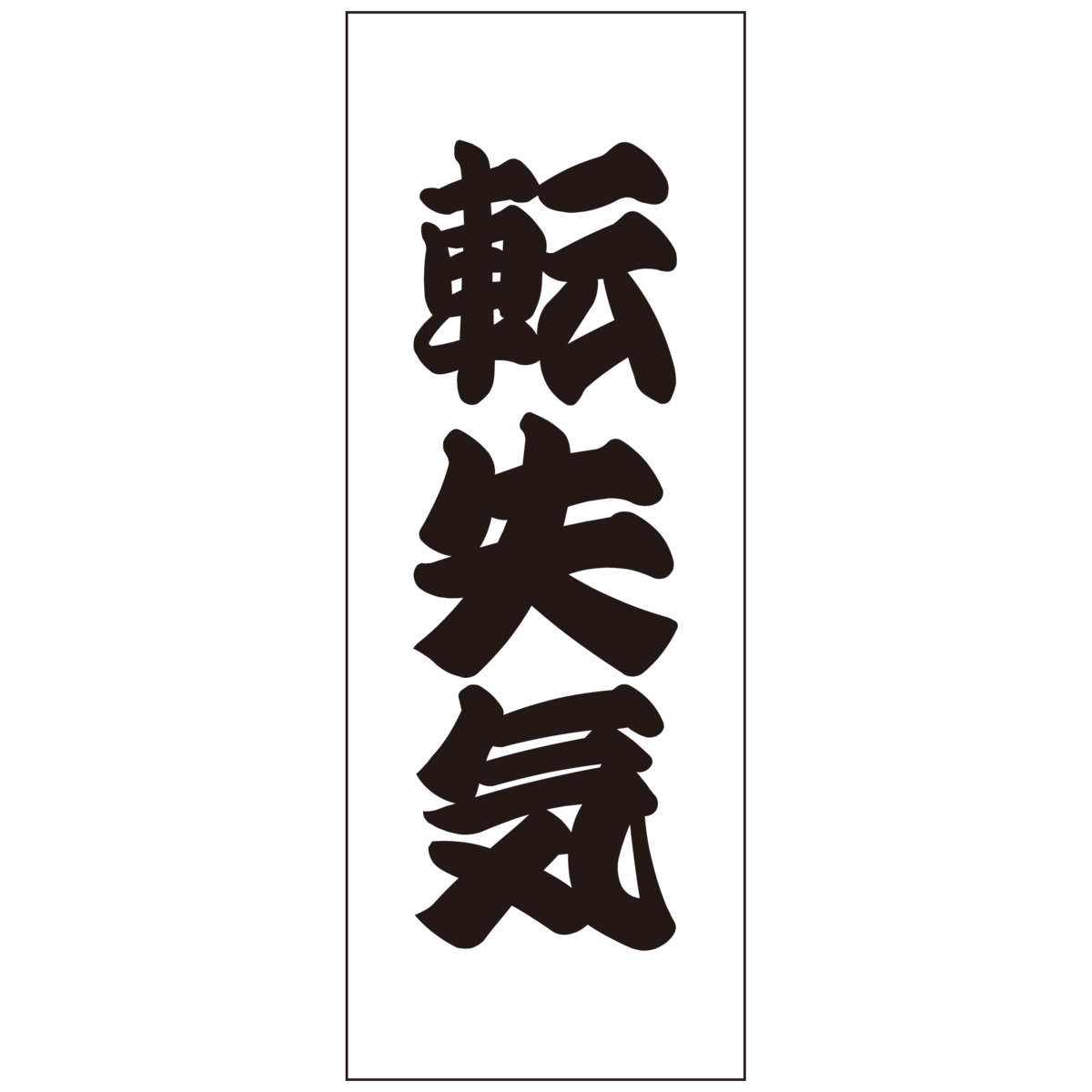
てんしき(転失気)は知ったかぶりから生まれる悲劇の喜劇をテーマした古典落語の演目。
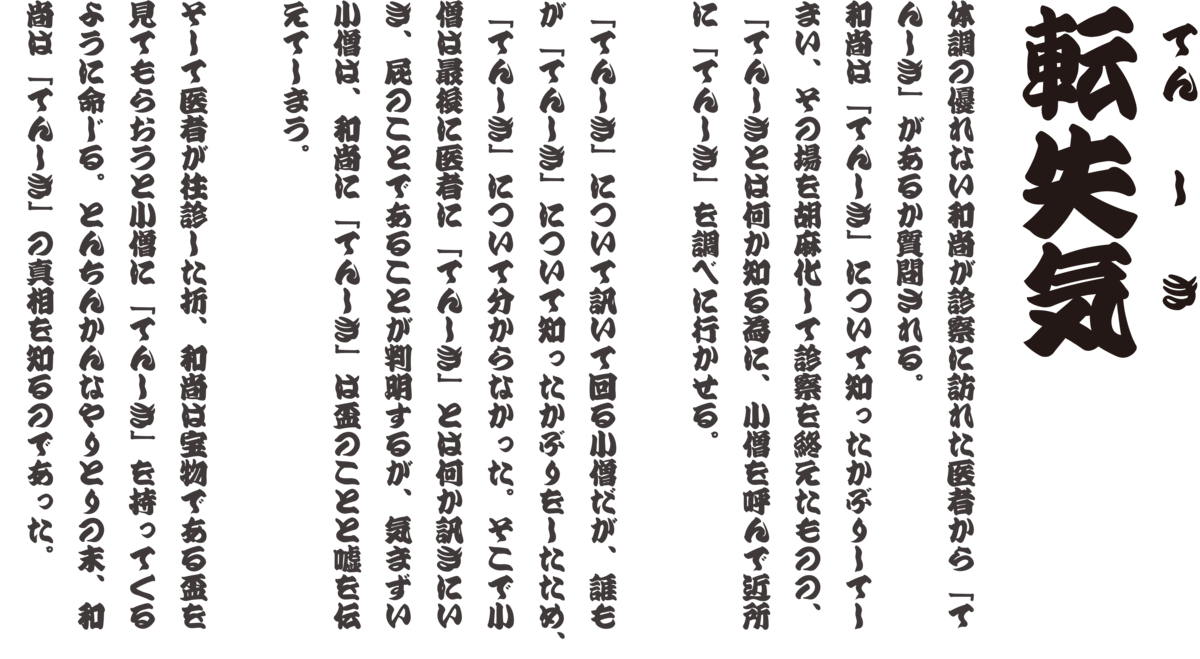
体調の優れない和尚が診察に訪れた医者から「てんしき」があるか質問される。
和尚は「てんしき」について知ったかぶりしてしまい、その場を胡麻化して診察を終えたものの、「てんしきとは何か知る為に、小僧を呼んで近所に「てんしき」を調べに行かせる。
「てんしき」について訊いて回る小僧だが、誰もが「てんしき」について知ったかぶりをしたため、「てんしき」について分からなかった。そこで小僧は最後に医者に「てんしき」とは何か訊きにいき、屁のことであることが判明するが、気まずい小僧は、和尚に「てんしき」は盃のことと嘘を伝えてしまう。
そして医者が往診した折、和尚は宝物である盃を見てもらおうと小僧に「てんしき」を持ってくるように命じる。とんちんかんなやりとりの末、和尚は「てんしき」の真相を知るのであった。
「らくごえほん てんしき」内容
子供だって大人だって「しらないこと」はたくさん。
つい知っているふりをしたり適当なことを言ってしまうと、どんどん大変なことになってしまいます。
ある日、お医者さまから「てんしきはあるか?」と尋ねられた和尚さん。
何のことかさっぱりわからなかった和尚さんですが、つい知っているふりをしてしまいます。
でも、「てんしき」について知っているふりをしてしまったのは和尚さんだけではなくて…
江戸文字の書体「寄席文字」のご紹介
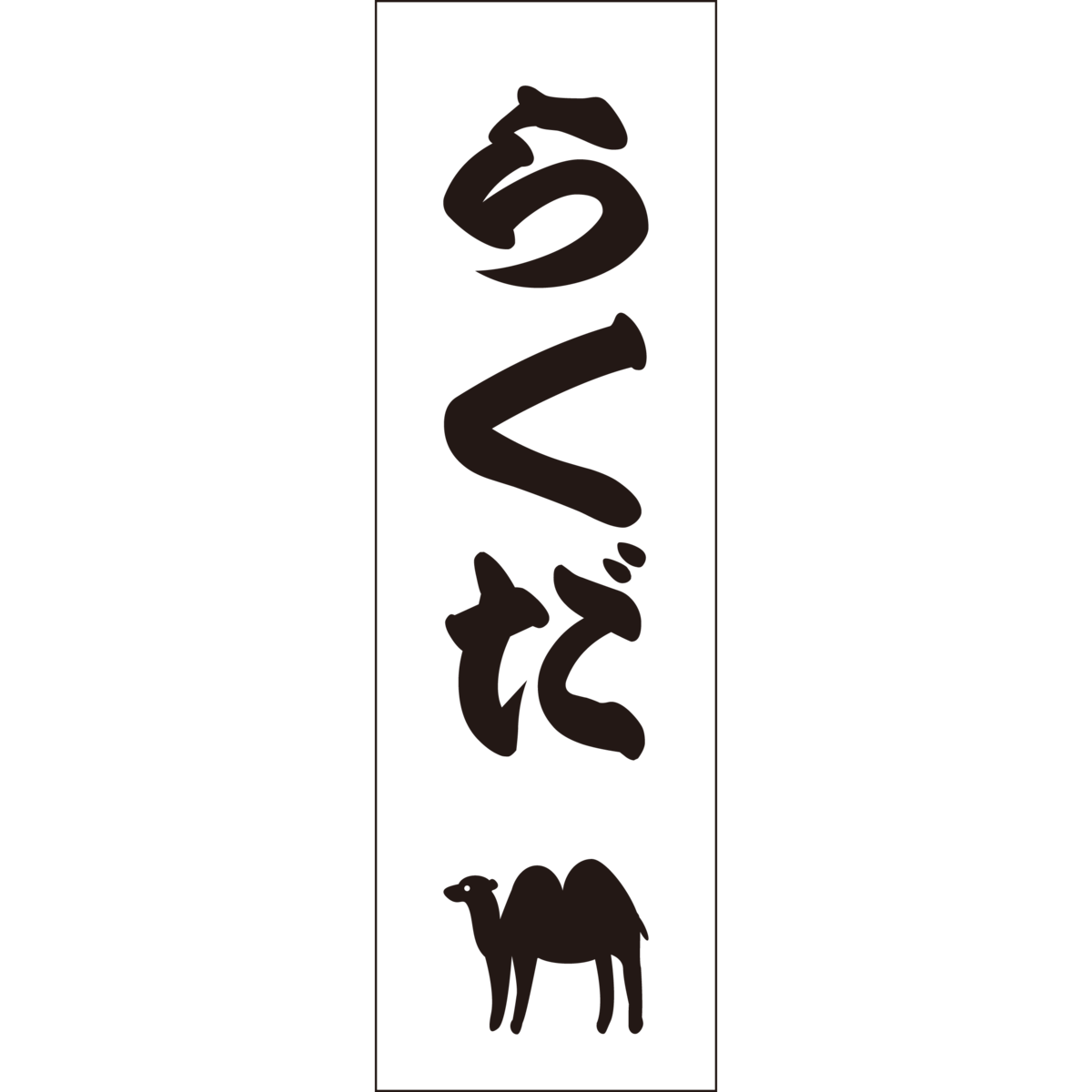
寄席文字は江戸時代に使用された図案文字である通称、江戸文字の一種。通称、橘流。
勘亭流と提灯文字を元になっており、客を寄せる意味を込めて縁起を担ぎ、字が詰まり加減になっているのが特徴。落語の看板やめくり、番付などに使用される。
使用書体はDC寄席文字。